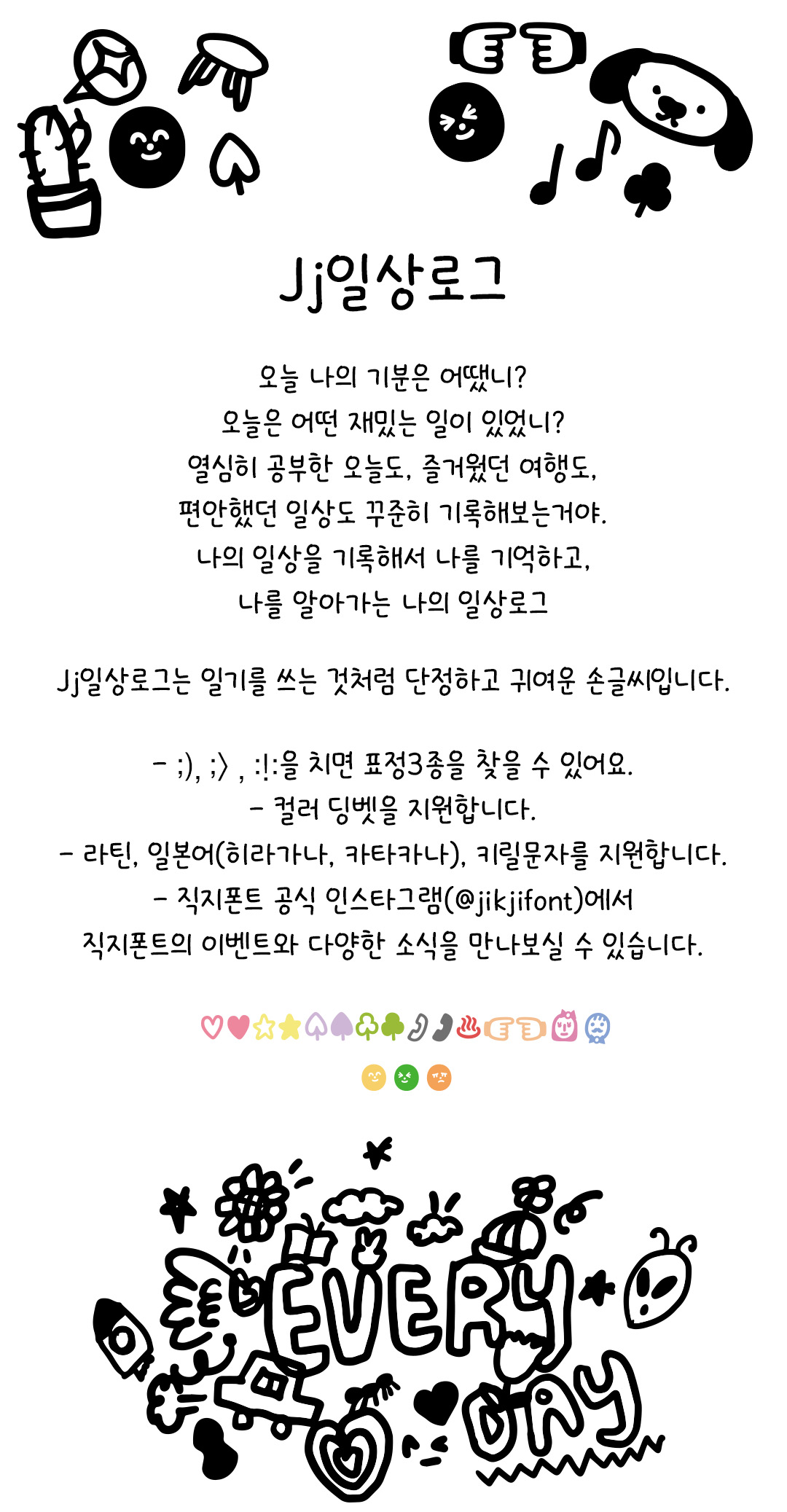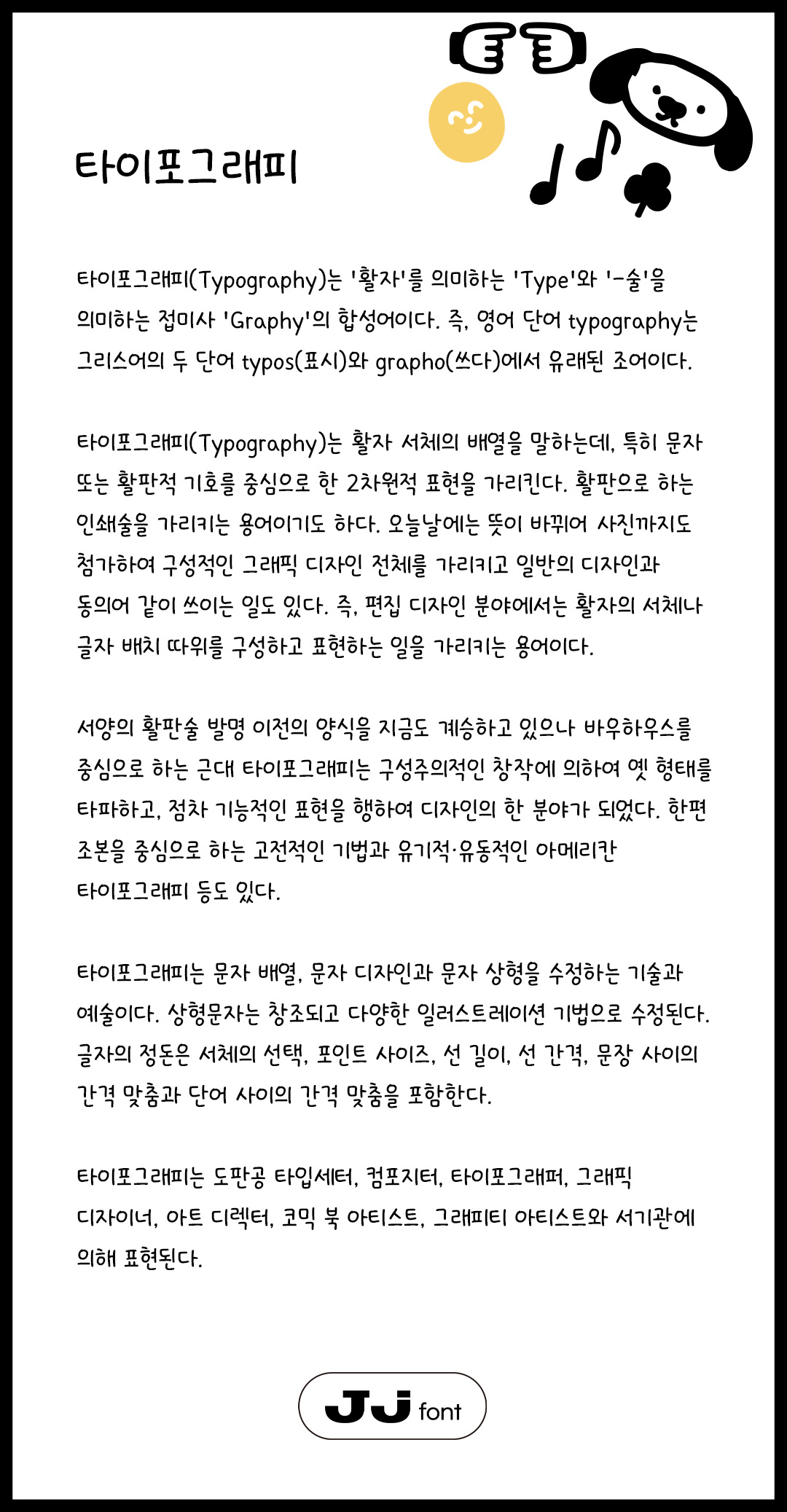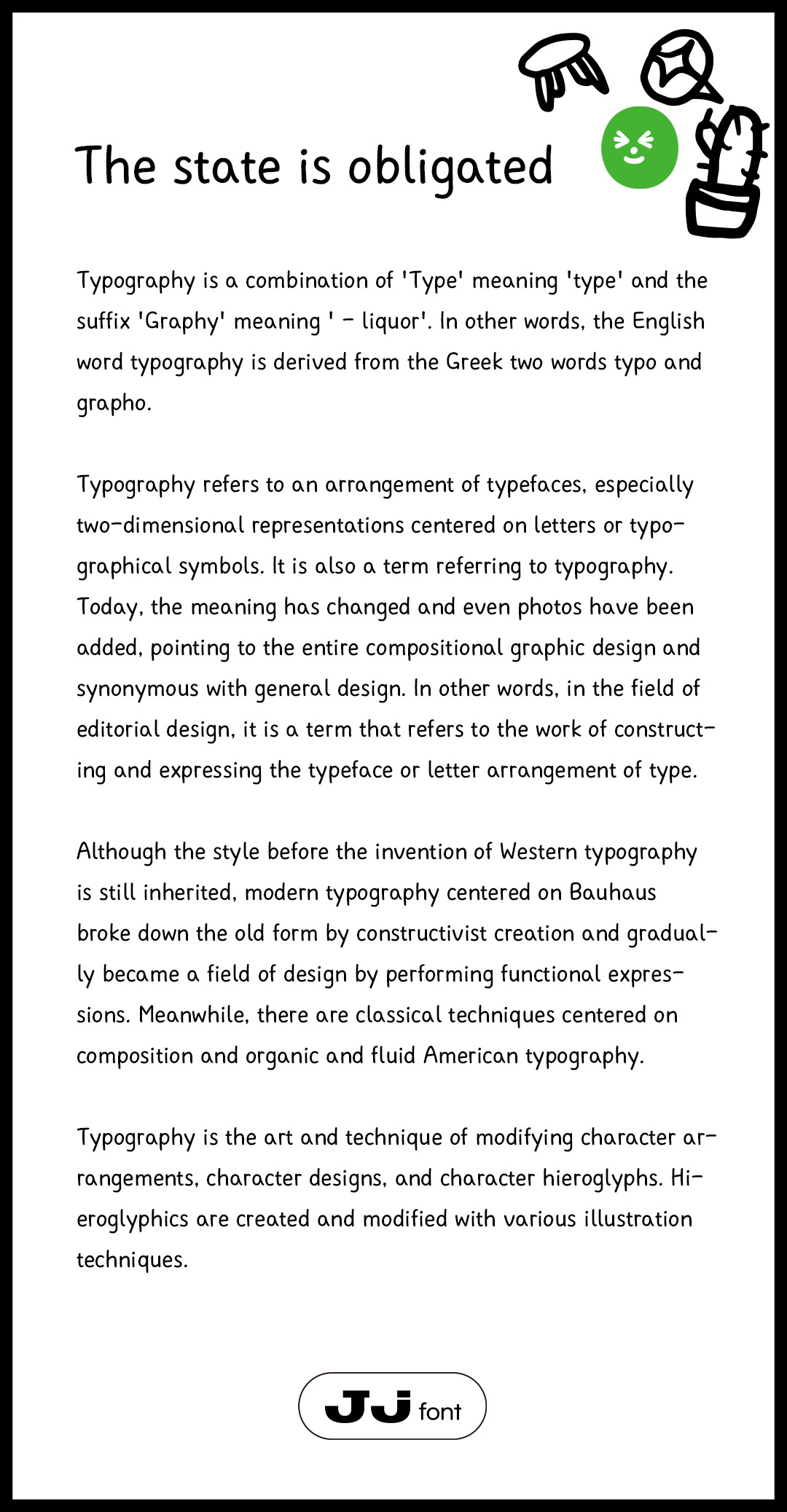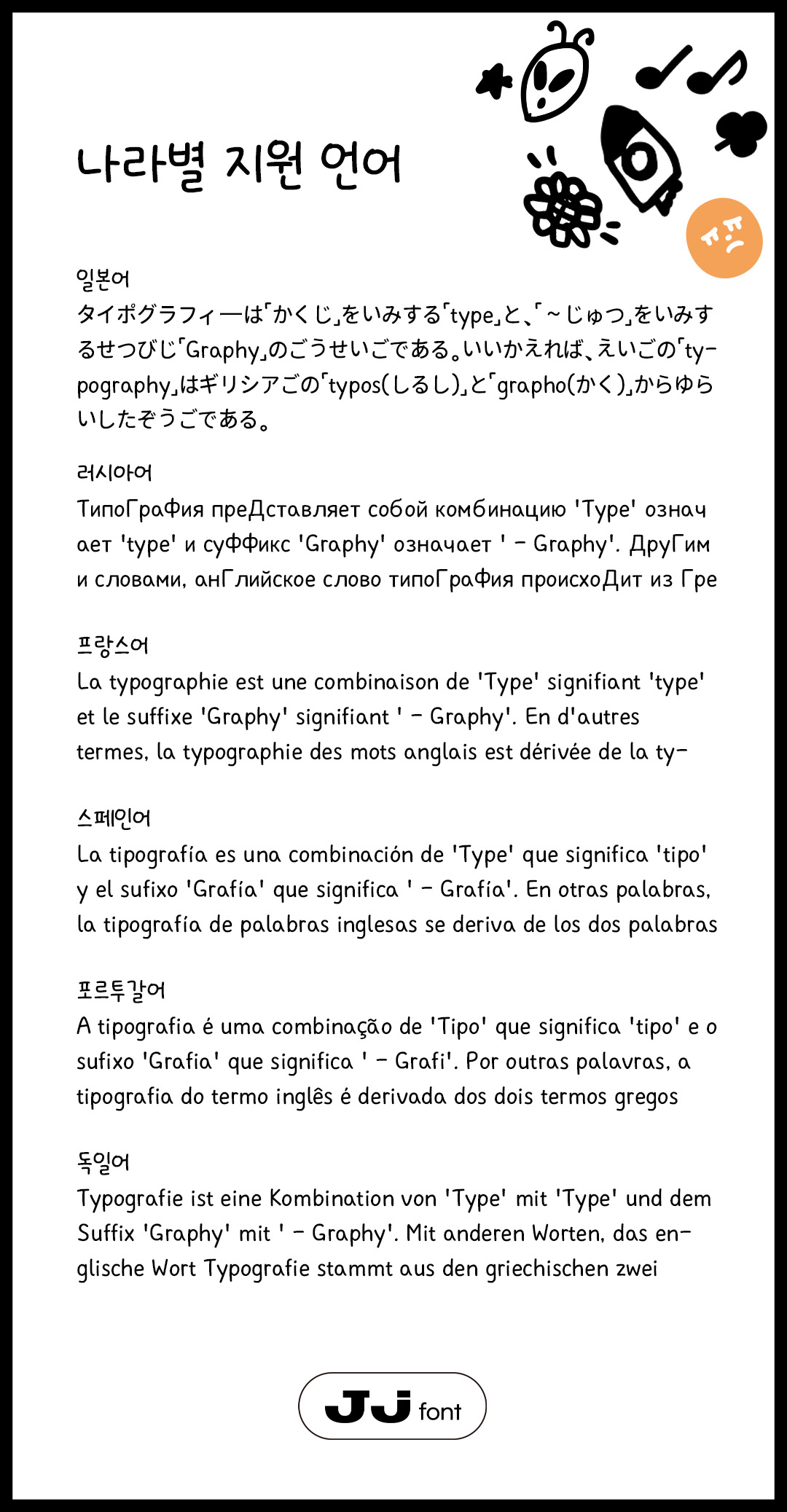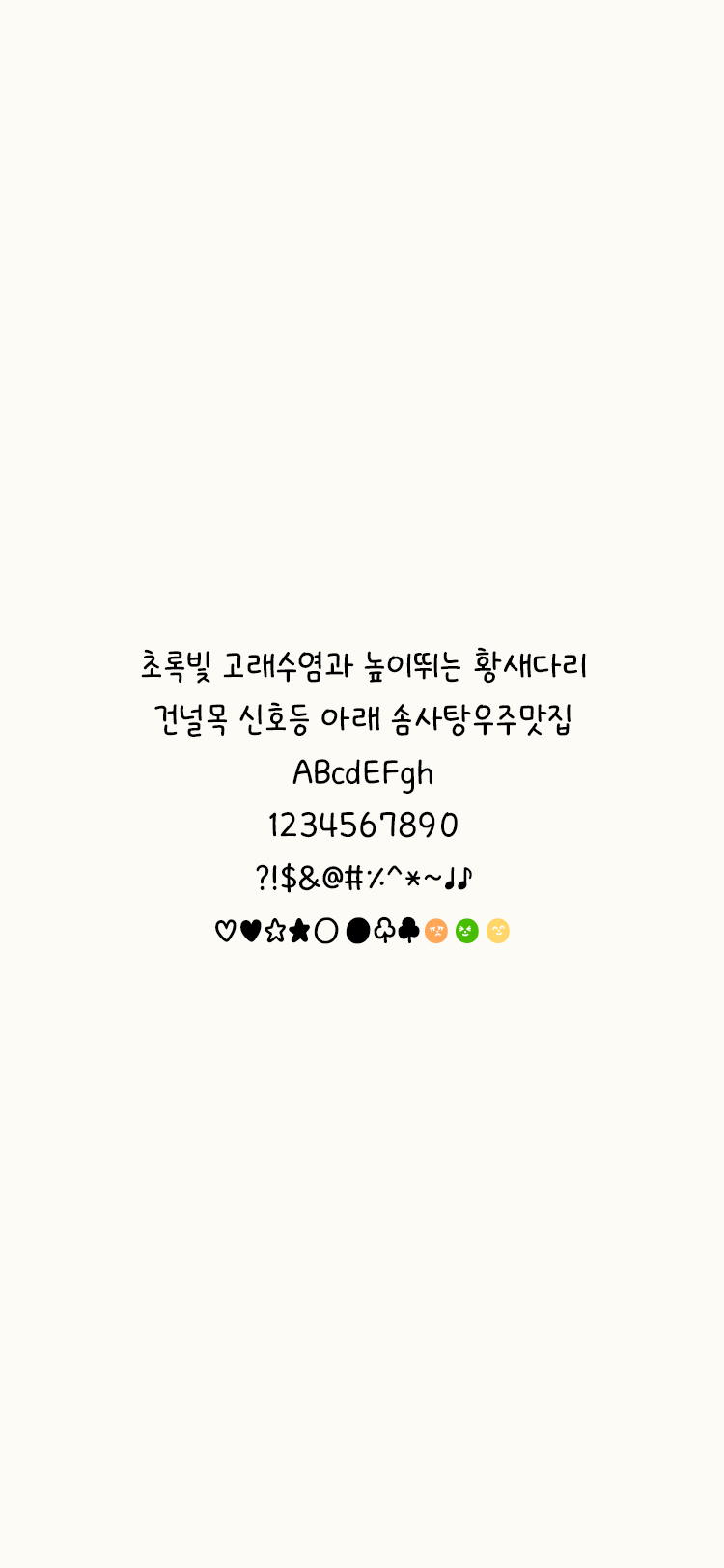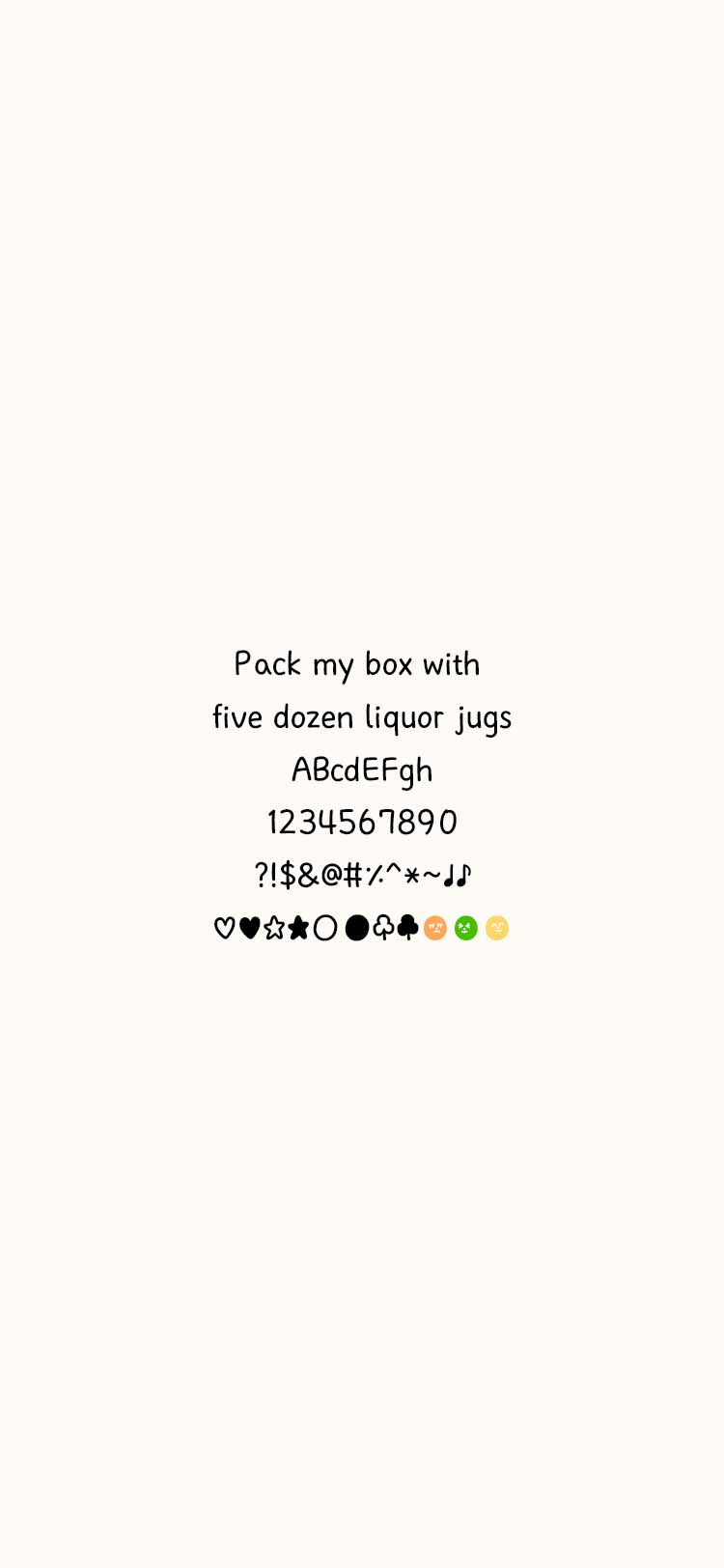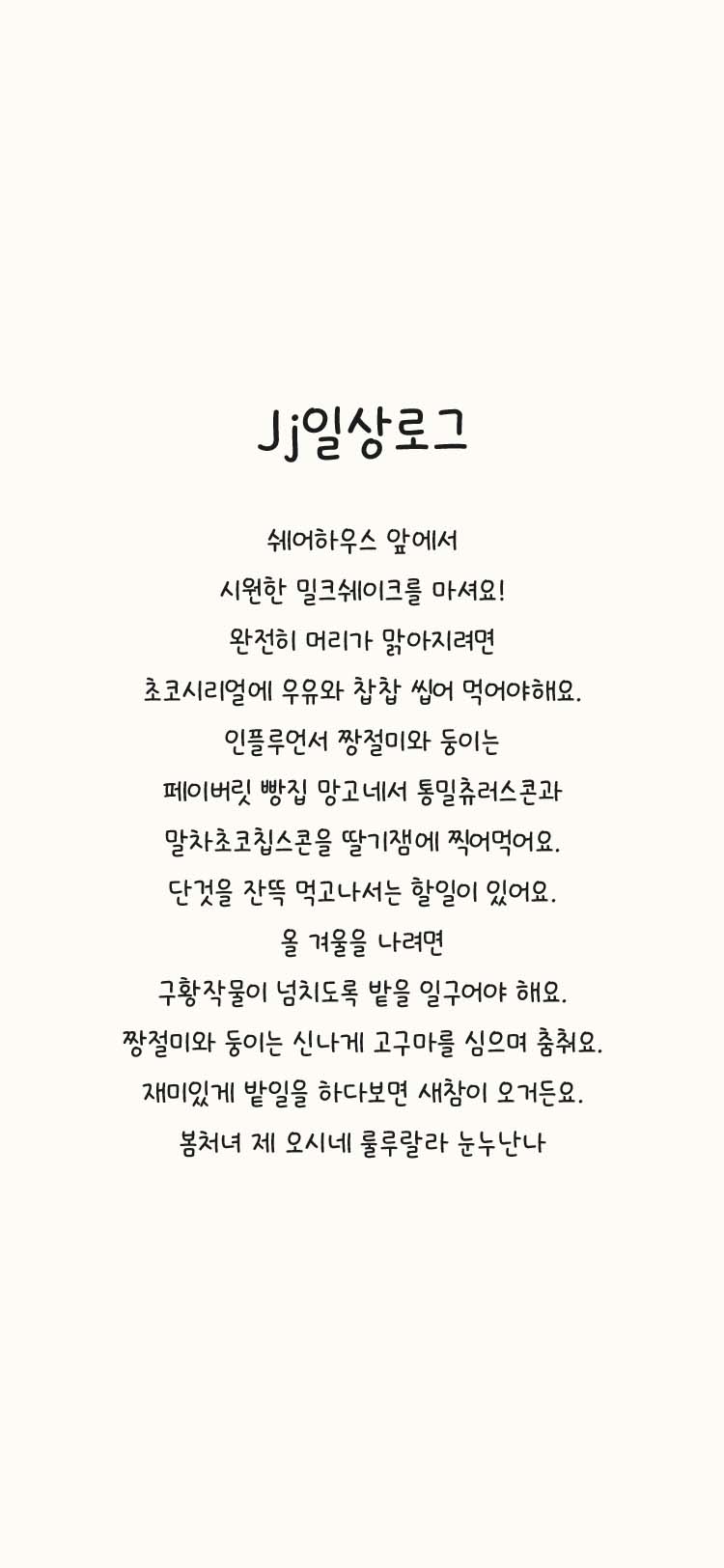
오늘은 어떤 재밌는 일이 있었니?
열심히 공부한 오늘도, 즐거웠던 여행도,
편안했던 일상도 꾸준히 기록해보는거야.
나의 일상을 기록해서 나를 기억하고,
나를 알아가는 나의 일상로그
< J일상로그 >는 일기를 쓰는 것처럼 단정하고 귀여운 손글씨입니다.
:!:을 치면 표정 3종을 찾을 수 있어요.
컬러 딩벳과 라틴, 일본어, 키릴문자를 지원합니다.
- Jj일상로그 / JjEverydayLog